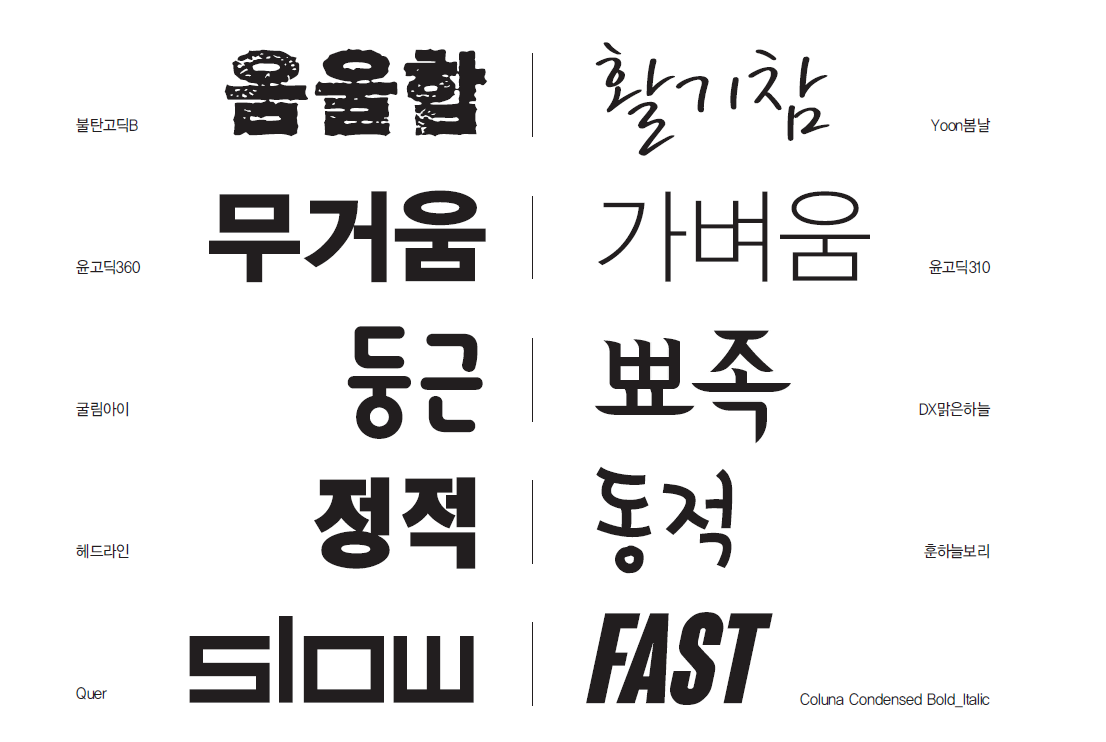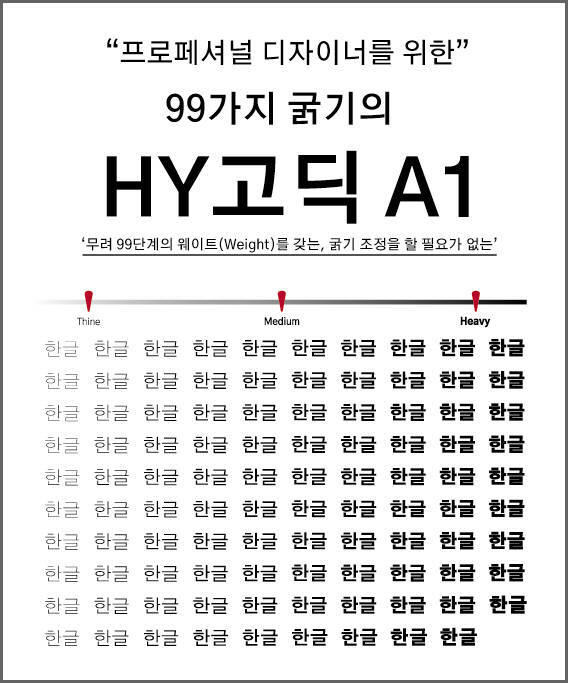
매력적적인 폰트를 선정하는 방법
1) 콘텐츠가 최우선
폰트와 상관없이, 내용이 충실한지 확인해야 한다.
아름다운 폰트가 빈약한 내용을 보정할 수 없다.
좋은 폰트는 읽는 사람이 내용에 집중할수 있도록, 글을 명확하게 만드는 것이다.
2) 최대한 적게 단순하게 유지
폰트는 상상을 초월할 정도로 많다.
수많은 폰트 때문에 오히려 압도당하기 쉽다.
너무 난무하지 않도록, 적당한 폰트 1~2개만 섞어서 사용하자.
주로 (제목, 본문) 2가지 폰트를 사용하는게 가장 효과적이다.,
3) 폰트가 다르면 대비를 봐라.
두개의 다른 폰트를 사용할 때 폰트의 대비가 명확한지 확인하자.
대부분 [굵게, 일반] 으로 표현할 수 있고, 많은 폰트들은 굵고, 얇은 서체를 함께 제공한다.
디자인은 쌍을 이루지만 두께감만 달라도 대비 효과가 좋아지며, 일관성이 생긴다.
만약, 더욱 강조하고 싶다면 약간의 컬러를 다르게 사용하자.
컬러는 시각적으로 디자인을 강조함으로 구조와 균형을 조심해야 한다.
4) 가독성이 제일 중요.
말할 필요 없이, 폰트의 최고 목적은 가독성이다.
폰트를 사용하는 목적과 맥락이 무엇인지 고민하자.
예를 들어 작은 화면에서 읽는 것인가? 아니면 진지한 내용의 글인가? 가벼운 내용인가?
사람들이 제목과 본문을 쉽게 구분할 수 있는가?
5) 폰트 집합 사이트 참조
폰트는 매우 많으며, 그것을 쉽게 비교할수 있는 홈페이지들이 많다.
Typewolf 같은 사이트는 폰트의 드랜드와 인기, 새로운 영감을 맛볼 수 있다.
미리 만들어진 다양한 홈페이지에서 폰트의 결과물을 확인하자.